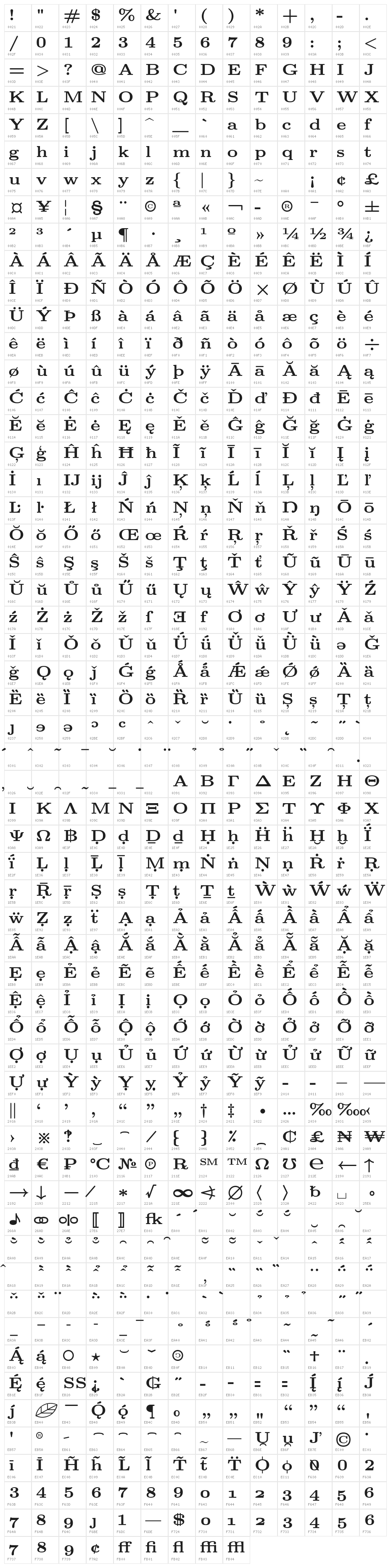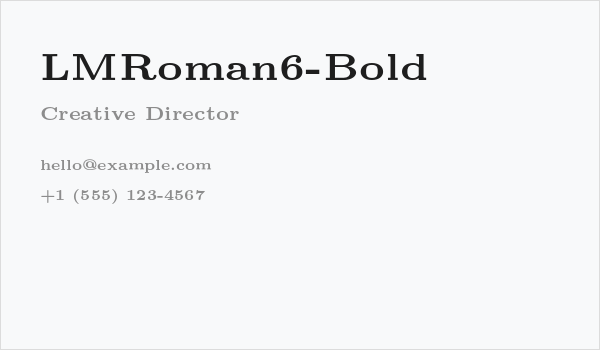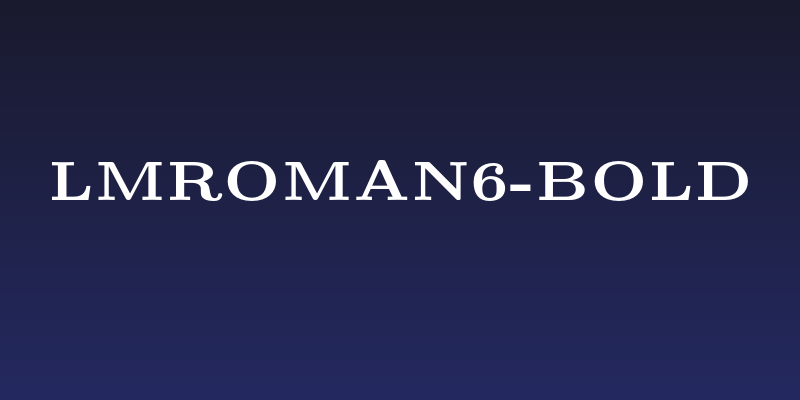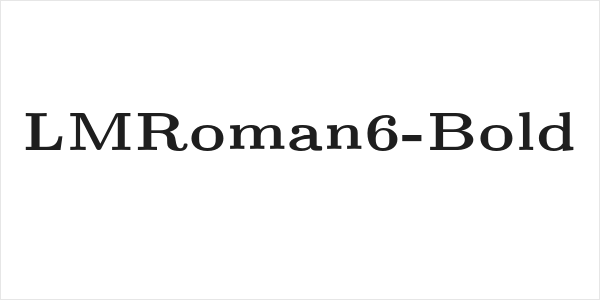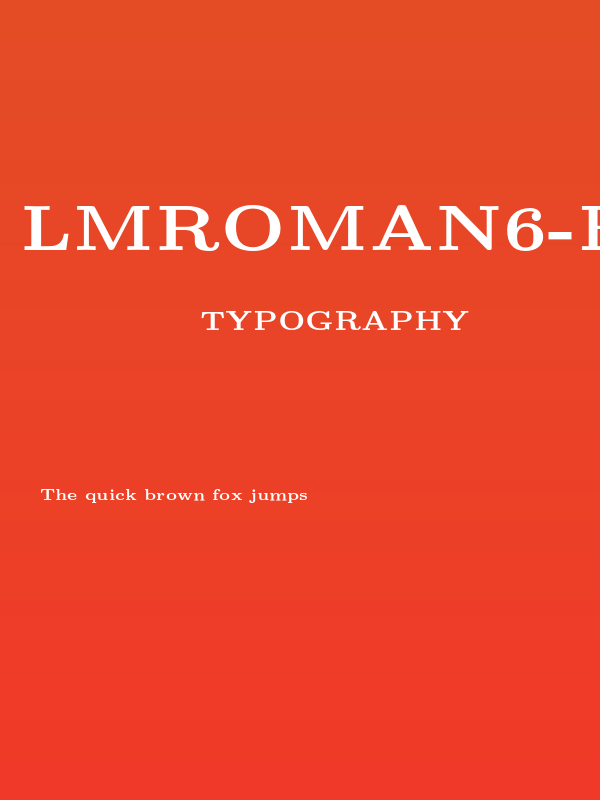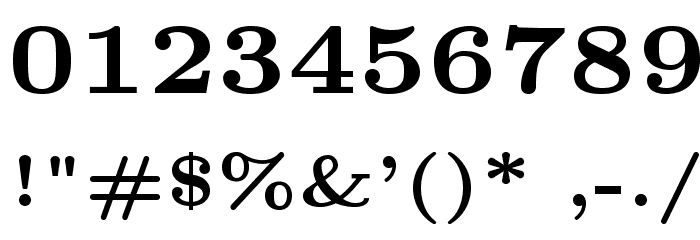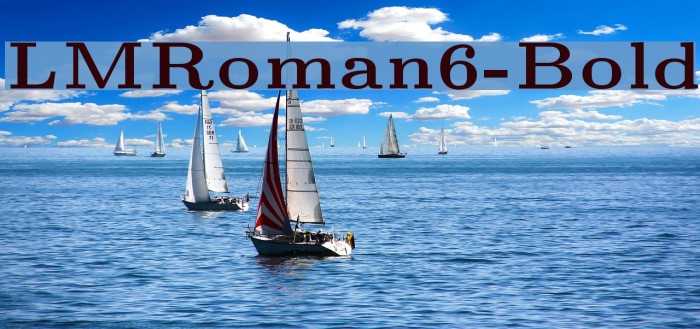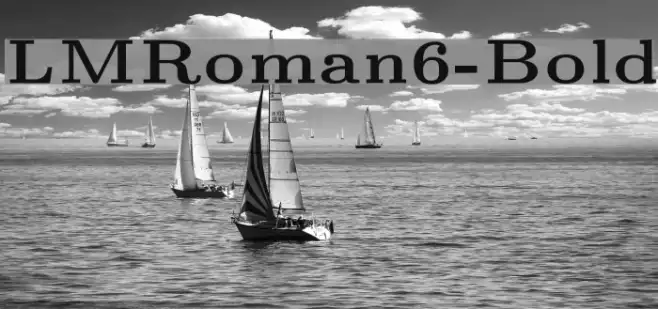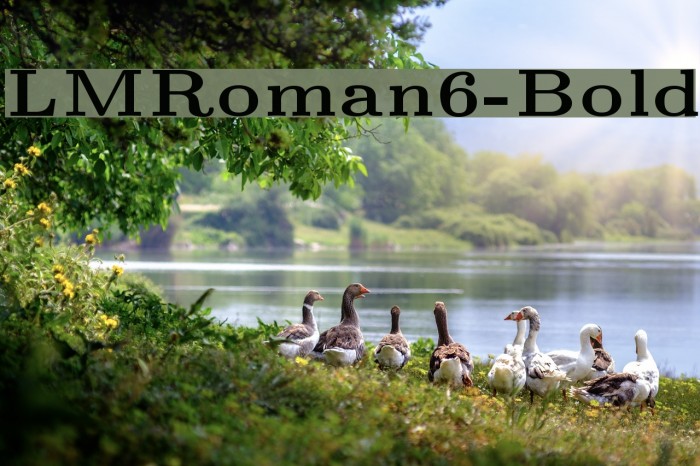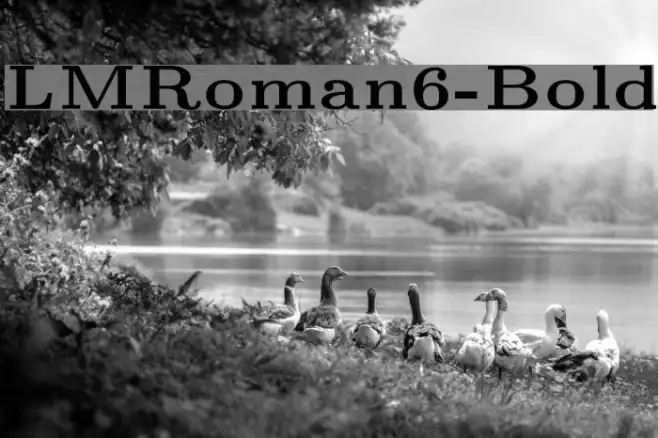
LMRoman6-Bold Font
| Progetti proposti | Ideal for book typesetting, formal invitations, academic publications, and branding materials that require a traditional and authoritative look. |